中英混排该用什么字体?企业宣传册呢?商业海报呢?
每款字体都有自己的性格,都有自己的“定位”
英文部分
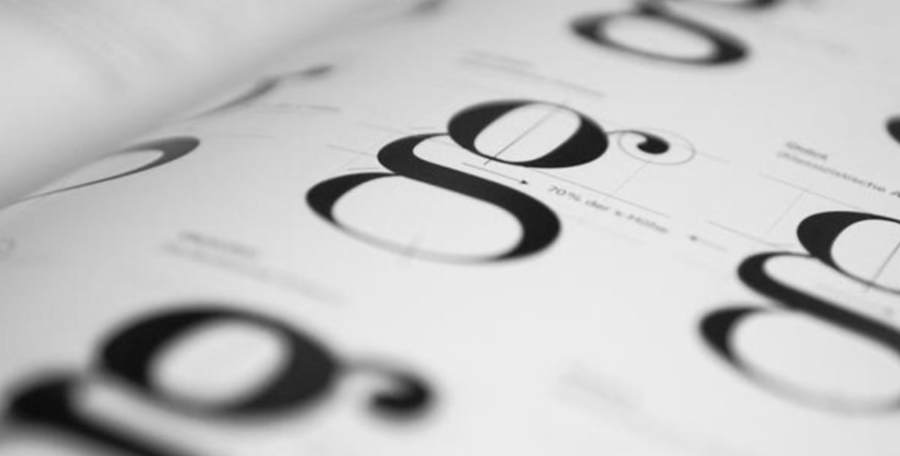
基本款推荐汇总 (历史古至今)
衬线体部分
Centaur 1470,半人马~三quer 了
史诗正统风格.威尼斯大教堂
数码化版本--Adobe janson pro
Garamond 16世纪 加拉蒙的
柔软罗马正体
Galliard 16世纪,加利亚德
阳刚罗马正体
Janson 17世纪,杨松
朴素粗旷罗马正体,阿姆斯特丹
Caslon 18世纪前叶,卡斯隆
美国/独立宣言所用,犹豫不决卡斯隆
Baskerville 18世纪后半叶,巴斯克维尔
英国当时不接受,后成为国家代表字
Copperplate Gothic 1915年 铜板印刷标志(Mac内建)
Slackers Gothic 无衬线版,巧克力店铺
Didot 19世纪初 迪多
女性化,数字是典型法国老式风格
Nicolas Cochin 铜板女性 19世纪
Cochin 铜板男性
均为迪奥商标
Snell Roundhand 1966 铜板草书体
Cartier商标
Bodoni 19世纪初 博多尼
意大利洗练罗马正体
Walbaum 19世纪 瓦尔鲍勃
工整充满无机感,大写四角衍生
Times
Times Roman 1932 贪污是罗马
英国报纸(times报) 专用,数码化后改版
Times ten 12pt以下排版
Palatine 萨拉厅
古典骨架,现代气息
多用于化妆品或高级商品,可与Bembo 和Ehrhardt排版
Trump Mediaeval 20世纪50年代 特仑普
简洁易读罗马体,锐利,文字复兴骨骼
Sabon 20世纪60年代 桑博
罗马洗练王,自动铸排机导致意大利斜体和小写字宽过大,数码化后Sabon next 变窄
Centennial 1986 百年
莱诺自动铸排机100周年,风格明快,杂志报纸
Swift 迅速
简练与Trump 相似,现代风格
Minion 侍从
Adobe通用王,适用历史性题材
Diotima 2008 泰迪熊
儿童产品稳和
无衬线体部分
Franklin gothic 19世纪 富兰克林哥特
强壮有力
Futura 1927德国 未来
古典风格骨架,奇妙现代特征
Lv商标
Gill Sans
超级大气,偏向英国风格,却在德国常见
工艺家Eric Gill碑文相通
Optima 奥普体玛
无衬线cos罗马正体,难以分类
适合标题和短文
罗浮宫使用,时尚界纤细和优雅代表
Helvetica 20世纪中叶 海薇缇卡
地表最强字体
Univers U内沃尔
简练版海薇缇卡
Eurostile 20世纪60年代
科幻性标题王
Syntax 20世纪60年代 语法
古典骨架,温柔感无衬线
Fruitier 追求功能性
数字超好分辨,机场地铁导视牌
Alphabet Metro 带有手工味
巴黎地铁随处可见
Avenir 20世纪前叶 艾文莉
当时德国活字条件受限,被迫将Future x高度打小,不锋利版Future
ITC Stones Sans. 无拘无束有机感
和Frutiger Syntax 一样的亲切温暖
功能款推荐汇总
亲近感
手写体
Zapfino 葡萄酒
Vladimir s cript 法国时装杂志
Caflisch s cript 意大利面
Caliban 腊肠零食
Present 花草茶
Dom Casual 儿童用品
潦草手写体
Wiesbaden swing 儿童问候卡片
Freestyle s cript 旅游广告
Smudger 坚果包装
k
Cezanne 点心包装
促进食欲
无衬线
Cronos 酱汁料包
ITC Highlander 威化饼干
Goudy Sans 辣椒调料
Woodland 水果酸奶
实惠感
Flora 牛奶
Textile 果茶包装
FF Tartine s cript 麦片
Spring 饼干包装
Mistral 乳制品包装
英国风
Big Caslon 样本册
Palace s cript 红茶产品
Windsor 服装店
Thorowgood 金属活字印刷
New Johnston 伦敦地铁宣传
ITC Johnston 伦敦交通系统
Albertus 伦敦导路牌
Gill Sans 英国王
Perpetua 雕刻的碑文
德国风
Wilhelm Klingspor Gotisch 阳刚报纸标题
Duc Dc Berry 咖啡馆外墙
Wittenberger Franktur 药店招牌
FF Meta 德国铁道
TheSans 德国电视台
Stempel Garamond 德国小说正文
Din 识别性高 德国高速公路
法国风
Auriol 蜂蜜产品
Arnold Boecklin 小咖啡馆
Linos cript 蜜蜂标签
Cochin 菜单
Antique Olive 电影标题
Banco 法国肉店
Mistral ,Choc 休闲风格
Vendome 罗马气息
Peignot 安色尔体
信赖感
Helvetica 明信片
Univers 银行企业
Futura 阅览室
Vectora 购物中心
Frutiger 英国空港
新无衬线
Vialog 慕尼黑市政交通系统
TheSans 瑞士电话亭
ITC Officina Sans 医疗机构
小pt场合排版(如明信片,小宣传卡)
Times ten
Times Europa 大字怀
Bell Gothic---贝尔电话本专用字
Bell centennial----百年庆取代了Gothic
Spartan Classified----小广告 5.5pt以下
Vectora----x-high极高
中文推荐部分(几乎全为上海印刷技术研究所)
陆华平,日本森泽国际排版一等奖
美丽体,综艺体(华康字库)
钱震之,现代美术研究所所长
柳叶体,美黑体,散点方角体,粗方仿宋
周今才,华文印刷顾问
行头宋体 1971年,吉宋体 1992年,黑一体 1961年,黑二体 1963年
徐学成 上海新知/人民出版社
新宋体 1987年 双饰美术 1984年 雅艺体 1998年 扁美术 1999年 饰艺体1999年
皱秀英 北京新华字模厂
汉仪字库 家书体 秀英体
齐立 上海印刷技术研究所
微软雅黑 2004年 倩体 1998年 剪纸体 2002年 超细黑(方正)2008年
兰亭黑 2008年 兰亭宋 2004年
硬楷体(日本森泽评审员奖)1990年 细楷体
柯炽坚 香港地铁公司
宋黑系列(monotype字库)
瘦金体(华康字库)1995年
俪宋体 俪黑体 超明 超黑 超圆
余秉楠 中国出版发行研究所
友谊体(辞海)德国的礼物
谢培元 全国印刷字体工作委员会
新报宋(方正字库)人民日报
细宋体(第一届全国字体评选会一等)1984年
隶书体(第一届全国字体评选会二等)1984年
宋一体(繁/简) 宋二体
钱焕庆 常州华文印刷公司
长仿宋 1967年
华文楷体 1922年
朱智伟
钢筋隶书 (挺拔有力)
北魏隶书 (硬朗流畅)
答主最多使用(极不理智)
思源黑体,汉仪旗黑,方正兰亭刊黑
明石体,小塚明朝,光朝体,秀英明朝,筑紫明朝
白舟白羽书体